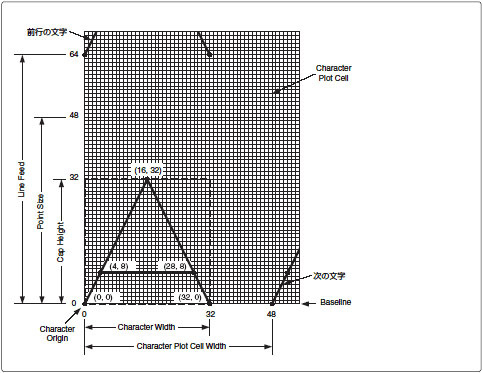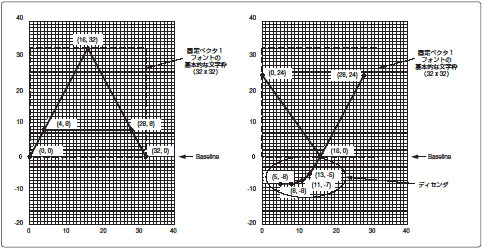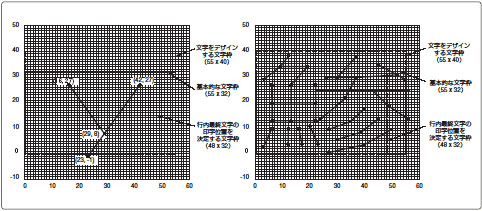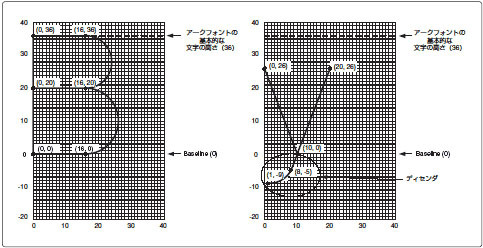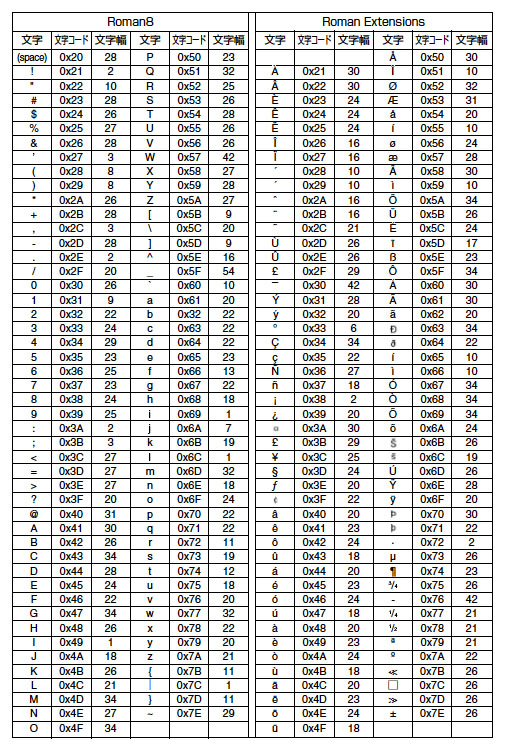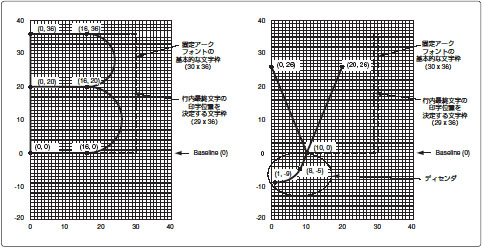
フォント
本エミュレーションモードでは、Stickフォントを使用して一連の直線と円弧(ベジェ曲線)で描画することができます。
本エミュレーションモードで印字できるのは、Stickフォントのみです。BitmapフォントやScalableフォントを使用することはできません。
Stickフォントの種類
文字セット
本エミュレーションが搭載しているStickフォントの文字セットは、以下の23種類です。
タイプフェース
本エミュレーションが搭載しているStickフォントのタイプフェースは、以下の3種類です。
ベクタフォント:
文字を直線のみで描画するフォント
ドラフティングフォント:
文字を直線のみで描画するフォント
アークフォント:
文字を直線と円弧で描画するフォント
DJ800と本エミュレーションのドラフティングフォントでは、デザインが異なります。
文字ピッチ
本エミュレーションが搭載しているStickフォントの文字ピッチは、以下の2種類です。
固定ピッチフォント:
全ての文字の文字幅が同じであるフォント
可変ピッチフォント:
文字ごとに文字幅が異なるフォント(たとえば、「M」の文字ピッチは大きいが、「i」の文字ピッチは小さいなど)
内蔵フォント
本エミュレーションが搭載している内蔵フォントは、以下の5種類です。
固定ベクタ1フォント
固定ベクタ3フォント
固定ドラフティング2フォント
固定アークフォント
可変アークフォント
* JIS Kanji-1はJIS90の第一水準漢字のみサポートしている文字セットです。また、JIS Kanji-2はJIS90の第一水準漢字と第二水準漢字をサポートしている文字セットです。
本エミュレーションモードとHP Designjet 800では、文字セットによって内蔵フォントが異なるため、印刷結果が若干異なります。詳しくは、付録の「HP-GL/2モードの注意と制限」を参照してください。
Stickフォントの構成要素
ここでは、Stickフォントの文字の構成要素について、固定ベクタ1フォントを例に説明します。
1文字が占める空間はCharacter Plot Cell(CPセル)と呼ばれる矩形領域です。CP Cell Width(CPセル幅)は1文字印字した後の文字原点の移動量であり、Line Feed(CPセル高)は改行した後の文字原点の移動量です。以下にCPセルの構成要素について説明します。
構成要素名
説明
Character Origin(文字原点)
CPセルの左下隅
Baseline(ベースライン)
基本的な文字の一番下の線
Character Width(文字幅)
基本的な文字枠の幅
Cap Height(文字高)
基本的な文字枠の高さ
CP Cell Width(CPセル幅)
現在の文字の文字原点から次の文字の文字原点までの長さ
Line Feed(CPセル高)
現在のベースラインの位置から次行のベースラインまでの長さ
Point Size(文字のポイントサイズ)
ポイントサイズ= 基本的な文字高 + ディセンダの深さ
可変ピッチフォントの文字サイズはポイントサイズで決まる
各フォントの構成要素の値は以下のとおりです。(単位はグリッド)
*1
固定ベクタ2フォント、固定ベクタ3フォント、固定アークフォントでは、LBコマンドの行内最終文字とSMコンドの印字文字の文字幅だけはそれ以外の文字の文字幅と異なるグリッド数で計算し、印字位置を決めています。これは印字位置を決める際の仕様であり、実際の文字は基本的な文字幅で印字します。たとえば、LO9で固定ベクタ2フォントを印字すると、カレントペン位置よりも7グリッド分だけ右側にはみ出て印字されます。
*2
可変アークフォントの文字幅は文字ごとに異なります。ただし、可変アークフォントの基本的な文字幅は28グリッドです。スペース、タブの文字幅とSI/SRコマンドによって指定する文字幅は28グリッドであり、LOコマンドのパラメータで11~19を指定したときのオフセット量は28グリッドの1/2(14グリッド)であり、DVコマンドによって縦置きを指定したときの改行ピッチは28グリッドの2倍(56グリッド)です。
固定ベクタ1フォント
固定ベクタ1フォントの文字は基本的に32×32のグリッドの文字枠にデザインされています。文字によってはバランスをとるため基本的な文字枠を上下左右にはみ出してデザインしている文字もあります。基本的な文字枠の一番下の線を「Baseline(ベースライン)」と呼びます。たとえば、「g」、「j」、「y」などの文字の一部はベースラインを下にはみ出してデザインされています。このとき、ベースラインより下にはみ出ている部分を「ディセンダ」と呼びます。以下は固定ベクタ1フォントの「A」と「y」のデザイン例です。
固定ベクタ2フォント
固定ベクタ2フォントの文字は55×40のグリッドの文字枠にデザインされています。
文字によってはバランスをとるため文字枠を上下左右にはみ出してデザインしている文字もあります。固定ベクタ2フォントには、固定ベクタ1フォントにあるベースラインとディセンダの概念はありません。55×40の文字枠は文字をデザインするためだけに使用しており、基本的な文字枠は55×32グリッドです。ただし、LBコマンドの行内最終文字とSMコマンドの印字文字だけは48×32グリッドの文字枠を使用して印字位置を決定し、印字します。以下は固定ベクタ2フォントの「y」と「鯵」のデザイン例です。
固定ベクタ3フォント
固定ベクタ3フォントの文字は127×127のグリッドの文字枠にデザインされています。
127×127の文字枠を55×40の文字枠に変換し、固定ベクタ2フォントと同じように取り扱います。55×40の文字枠に変換した後の文字データは座標値が少数値となります。
固定ドラフティング1フォント
固定ドラフティングフォントの文字は固定ベクタ1フォントと同様に基本的に32×32のグリッドの文字枠にデザインされています。固定ドラフティング1フォントと固定ベクタ1フォントは文字枠の取り扱いは同じですが、デザインのみ異なります。
固定ドラフティング2フォント
固定ドラフティング2フォントの文字は32×32のグリッドの文字枠に小数値でデザインされています。したがって、各文字の各座標点はグリッド位置に適合しません。
可変アークフォント
可変アークフォントの文字高は36グリッドです。
可変アークフォントの文字幅は文字ごとに異なります。ただし、タブやスペースは1文字の文字幅を28グリッドとして扱い、SI/SRコマンドの文字幅(widthパラメータ)は28グリッドの文字幅を指定します。基本的な文字高の一番下の線を「Baseline(ベースライン)」と呼びます。文字によってはバランスをとるため基本的な文字高より上にはみ出したり、ベースラインよりも下にはみ出してデザインされたりする文字もあります。たとえば、「g」、「j」、「y」などの文字の一部はベースラインを下にはみ出してデザインされています。このとき、ベースラインよりも下にはみ出ている部分を「ディセンダ」と呼びます。以下は可変アークフォントの「B」と「y」のデザイン例です。
ダウンロードフォントは1バイトフォントです。つまり、character set 531(HP-GL Download)は1バイトフォントの文字セットです。
登録可能な文字コードは0x21~0x7Eであり、最大94文字を登録できます。
ダウンロード文字は固定ピッチフォントです。CPセルの各構成要素の値は固定ベクタ1フォントと同じです。
ダウンロード文字のX、Y座標値は-127~127の範囲の整数値を指定できます。つまり、基本的な文字枠は32×32ですが、その文字枠をはみ出してデザインできます。
ダウンロードフォントは固定ピッチフォントと同等に動作します。すべての文字属性(つまりsize, slant, direction, label origin)はダウンロード文字にも適用されます。
パラメータなしのDLコマンドにより、ダウンロード文字をすべて削除します。登録文字コードのみでX、Y座標値のないDLコマンドはその文字コードのダウンロード文字を削除します。また、INコマンド、DFコマンドでもすべてのダウンロード文字を削除します。
ダウンロード文字は、あくまで一時的に登録されるものです。したがって、ジョブ終了時にすべてのダウンロード文字は削除されます。